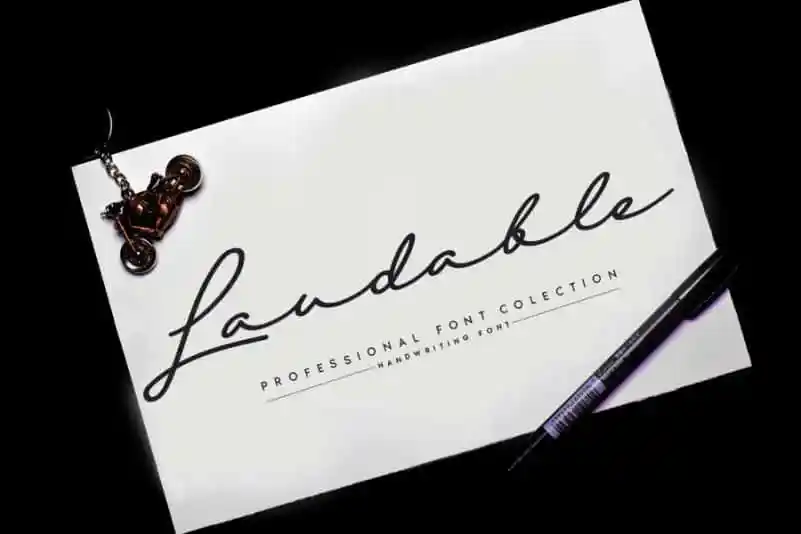
Laudable Script Font – Download Grátis
A Laudable Script Font é uma elegante escolha para quem valoriza a tranquilidade e o tempo passado à mão. Este estilo delicadamente relaxado e eterno se destaca como um recurso versátil que pode revolucionar sua estética de design. Seja em cartões de casamento, arte de assentos únicos ou postagens chama atenção nas redes sociais, a Laudable Script Font é perfeita para dar vida ao seu próximo projeto visual. Sempre haverá espaço para ela na paleta de suas criações criativas, desde as mais sutis até os designs mais audaciosos. Engane-se em apaixonar-se por esta fonte e faça dela uma parte essencial do seu design favorito.